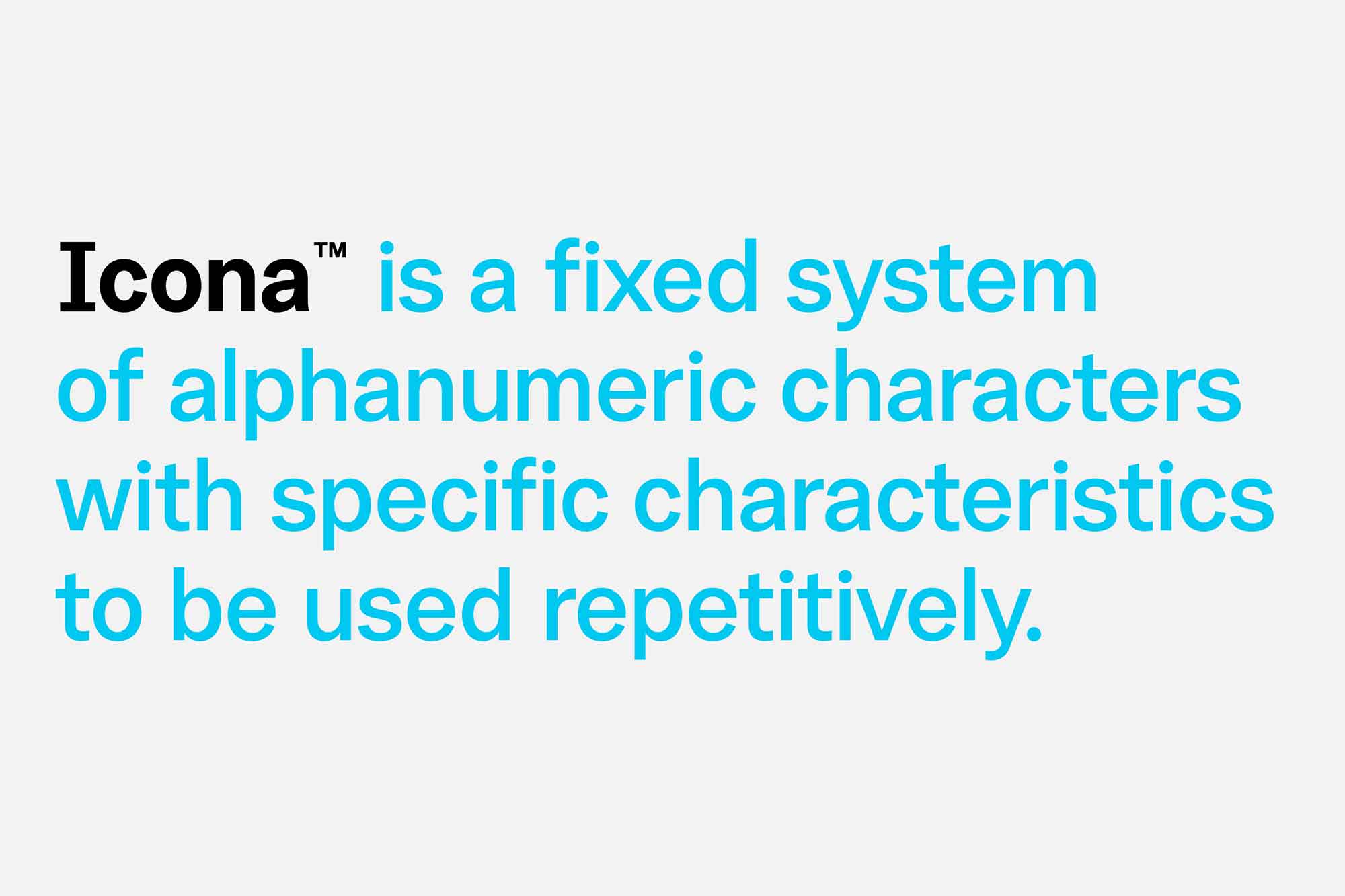
Icona Sans Font – Download Grátis
A Icona Sans é uma fonte única e minimalista, que oferece 8 pesos de negrito. Esta tipografia útil é perfeita para criações de marca, sites, publicações impressas e uma infinidade de outros usos em publicidade e embalagens. Suas versões em negrito regular e em itálico permitem que você faça design de uma maneira minimalista e atraente, ideal para trabalhos de marketing e design de embalagens. Com um estilo minimalista, a Icona Sans ajuda a destacar seus elementos de design em uma maneira simples e elegante. A fonte é perfeita para aquelas ocasiões em que você precisa de um design limpo e criativo para seu próximo projeto.